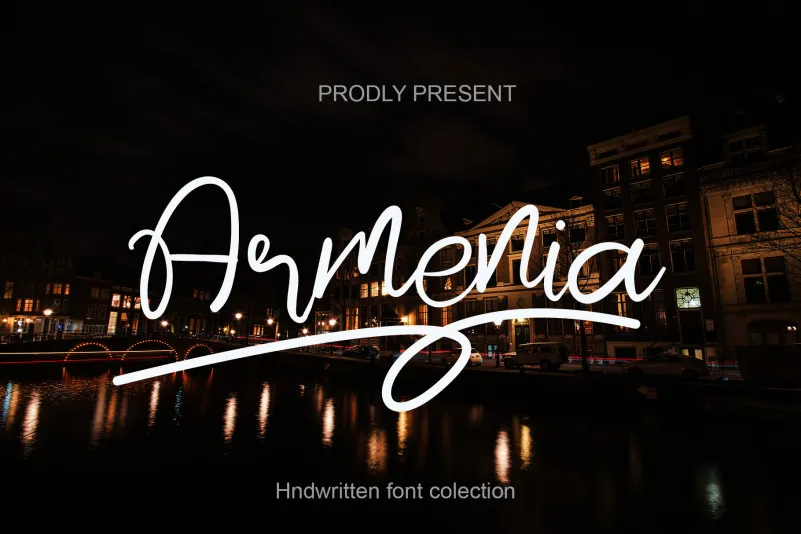
A fonte Armenia Font é perfeita para quem busca uma solução elegante e atemporal para projetos digitais. Embora seja uma tipografia feita à mão livre, cada letra possui um toque único e encantador que proporciona a sensação de vida em seu design. É ideal para criar logotipos memoráveis, identidades gráficas inovadoras e citações interessantes. Seja você um designer ou um criativo, o uso desta fonte é definitivamente uma escolha ótima para incrementar qualquer trabalho. Com seu estilo natural e envolvente, a Armenia Font se destaca como uma opção de primeira qualidade em nossa categoria de fonts feitas à mão livre.